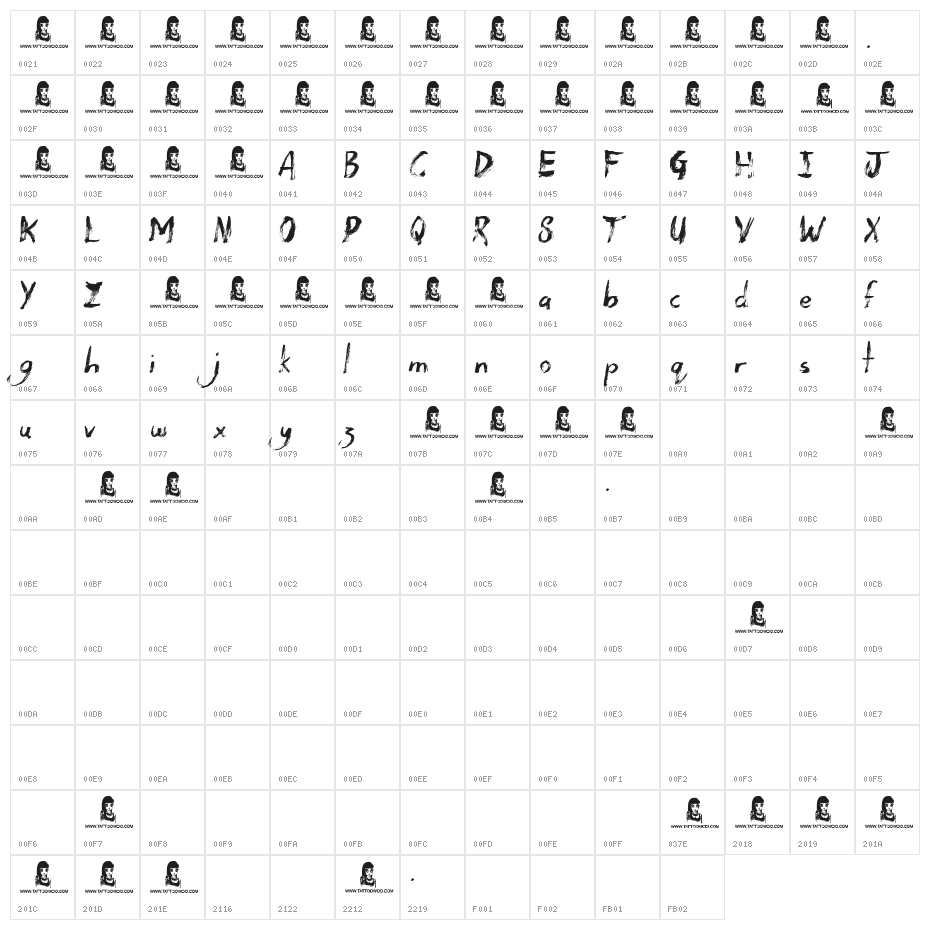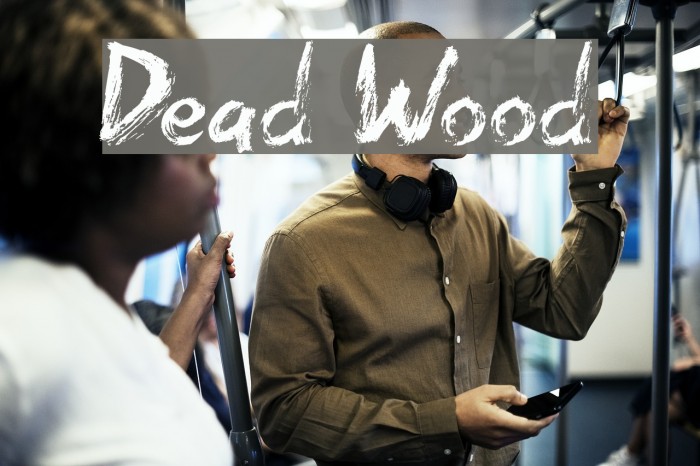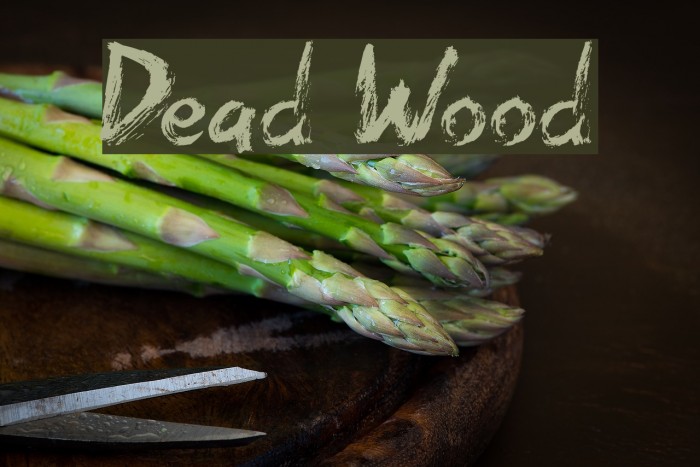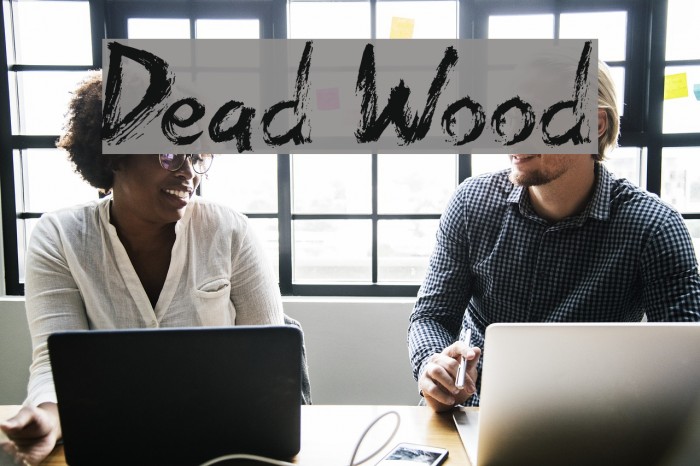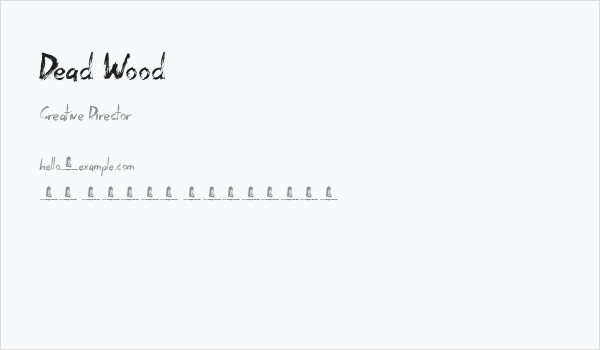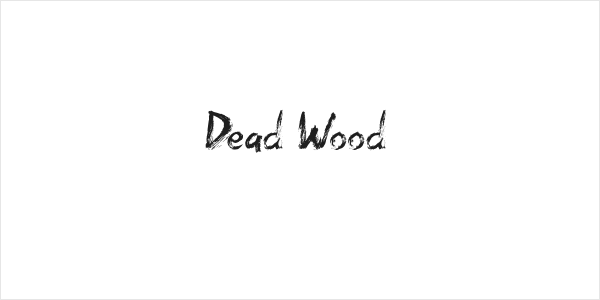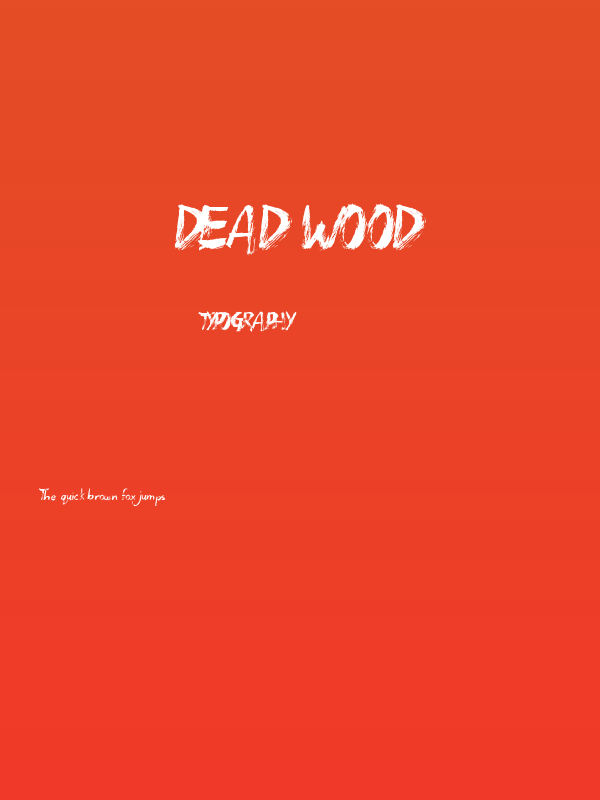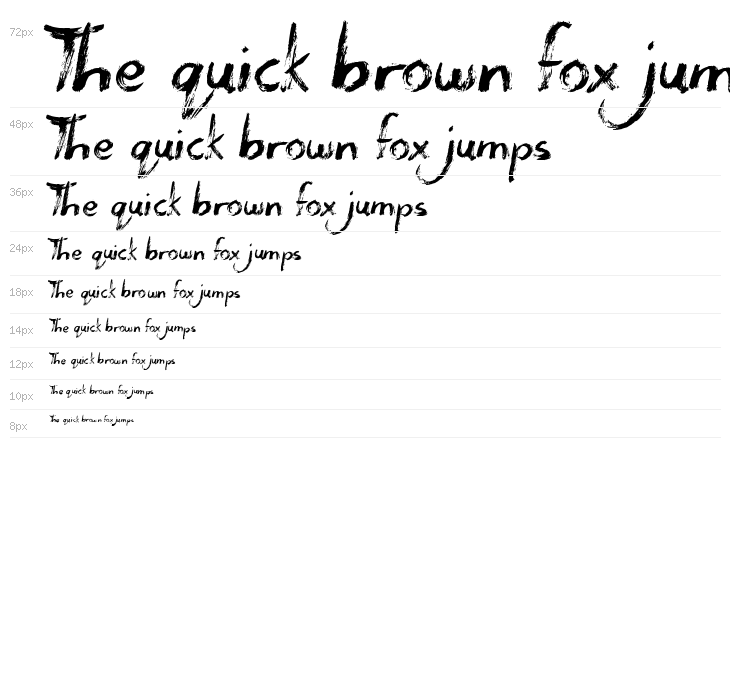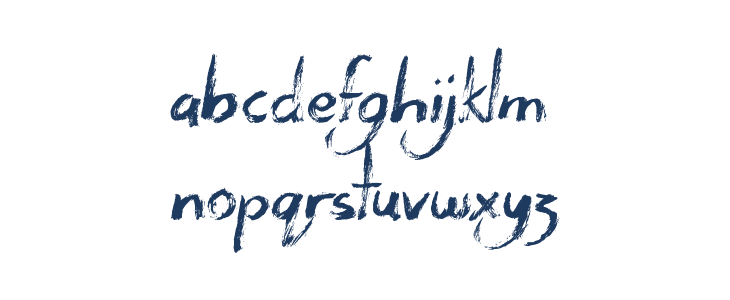
Dead Wood Font
✎ Thick
| Vorgeschlagene Projekte | Ideal for album covers, posters, branding for edgy or artistic products, and any design needing a bold, organic touch. |